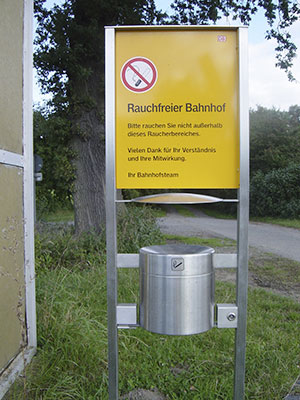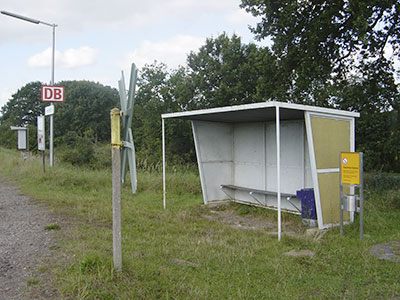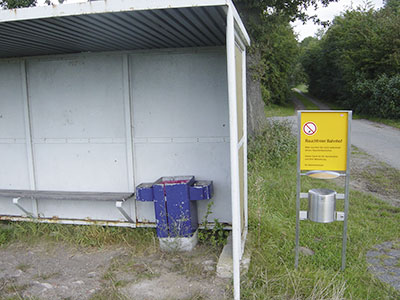
Fontnaepfchen 5: RaucherbahnhofTypografisch gibt es beim zitierten Hinweisschild kaum etwas auszusetzen,
allenfalls die Zeilenabstände sind zu groß. Doch bürokratisch
ist die Anlage ein Witz. Ein Schild, fast größer als die Bahnstation,
deklariert den Haltepunkt Neetzendorf als »Rauchfreier Bahnhof«. Dabei
steht das offene Häuschen mitten in der Heide, wo es sowieso schon schwer
ist, Passivraucher zur Weißglut zu bringen. Weiterlesen ...
![]() Eigentlich kein Fontnäpfchen sondern ein Fontschimmel ... Meine liebe
Kollegin Antje Dohmann von der PAGE hat mir diese drei Bilder ihrer
Heimat-Bahn-Haltestelle zugesendet und geschrieben: »Unser Dorf
Neetzendorf hat knapp 90 Einwohner aber einen eigenen Bahnhof. Dass dieser noch
nicht entsorgt wurde liegt vor allem daran, dass einmal im Jahr der Castor hier
lang fährt. Der Bahnhof besteht aus einem maroden Bushäuschen, es gibt
nicht mal einen Fahrkartenautomaten ... doch neuerdings ein Schild, dass ihn als
Nichtraucherbahnhof
ausweist.«
![]() Super-Schild, polierter Aschenbecher ... alles wind- und wetterfest ... ![]() ... neben einem Bushäuschen aufgestellt: der rauchfreie Bahnhof von Neetzendorf. ![]() Man beachte den alten, blauen Mülleimer mit integriertem Ascher ... und lasse sich die Unterzeichner auf dem neuen Schild – »Ihr Bahnhofsteam« – noch mal auf der Zunge zergehen Ein echter Schildbürgerstreich. Der Gedanke dahinter ist klar: die Bahn möchte mit Stolz einen großen Prozentsatz ihrer Bahnhöfe als Nichtraucher-Bahnhöfe ausweisen. Der Aufwand hierfür ist im Fall des Haltepunktes Neetzendorf gering ... und doch zu aufwendig, zu teuer und schlicht überflüssig. Herausgegeben: Mi - Oktober 26, 2005 at 01:52 nachm. | |